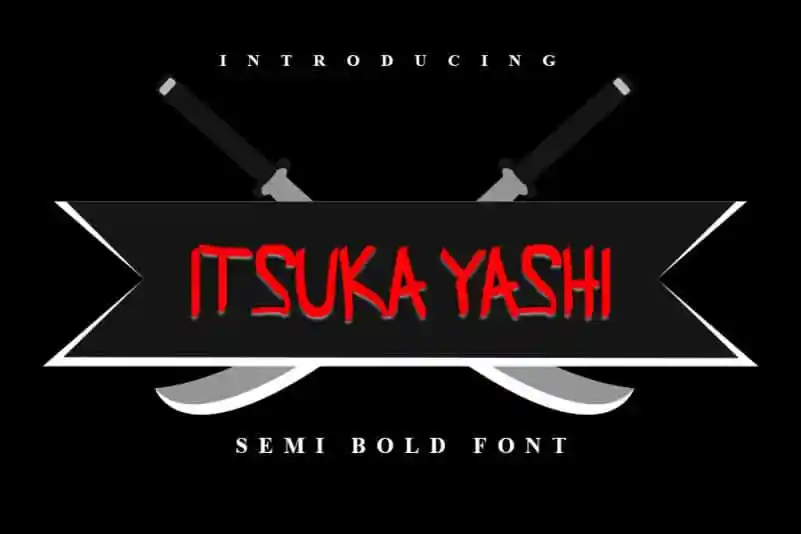
ITSUKA YASHI Display Font – Download Grátis
A ITSUKA YASHI Display Font é uma excelente escolha para designers que buscam misturar elementos tradicionais com modernidade. Inspirada nos traços elegantes da escrita japonesa, essa fonte mantém sua essência clássica ao mesmo tempo em que se mostra fresca e atual. Suas capacidades únicas fazem dela uma escolha perfeita para diferentes projetos de design gráfico, desde cartões de visita e títulos até cartazes e papelaria. Com ITSUKA YASHI Display Font, você pode explorar uma variedade imensa de ideias criativas sem sacrificar a elegância ou o impacto visual que sua marca precisa ter no mercado.